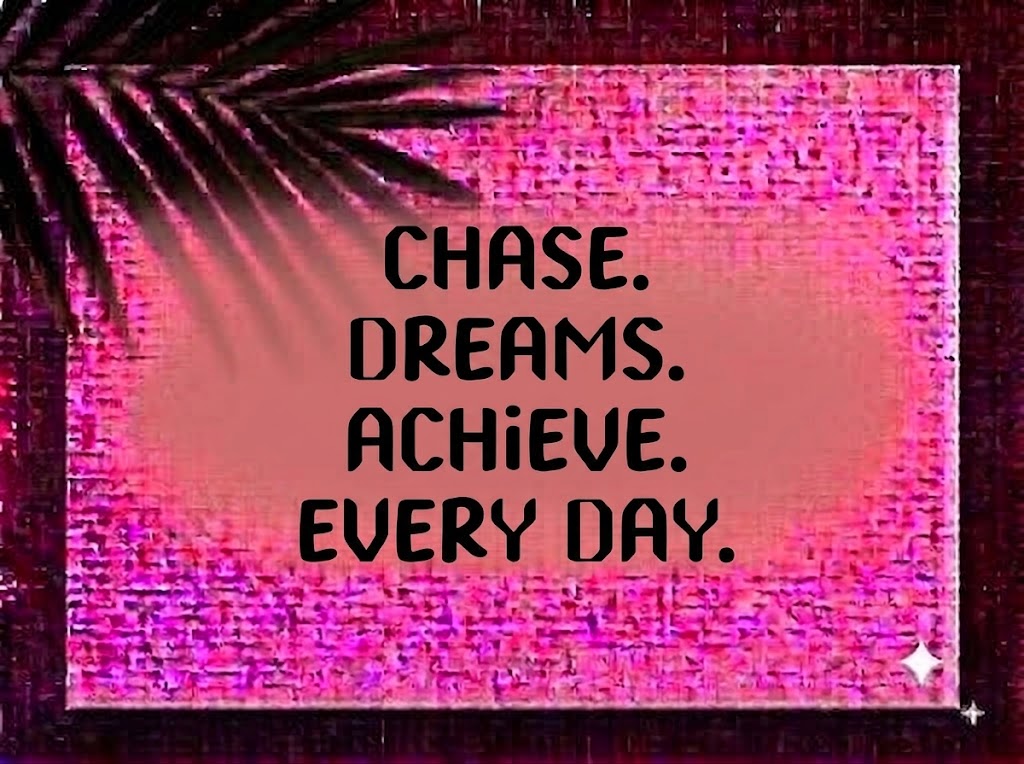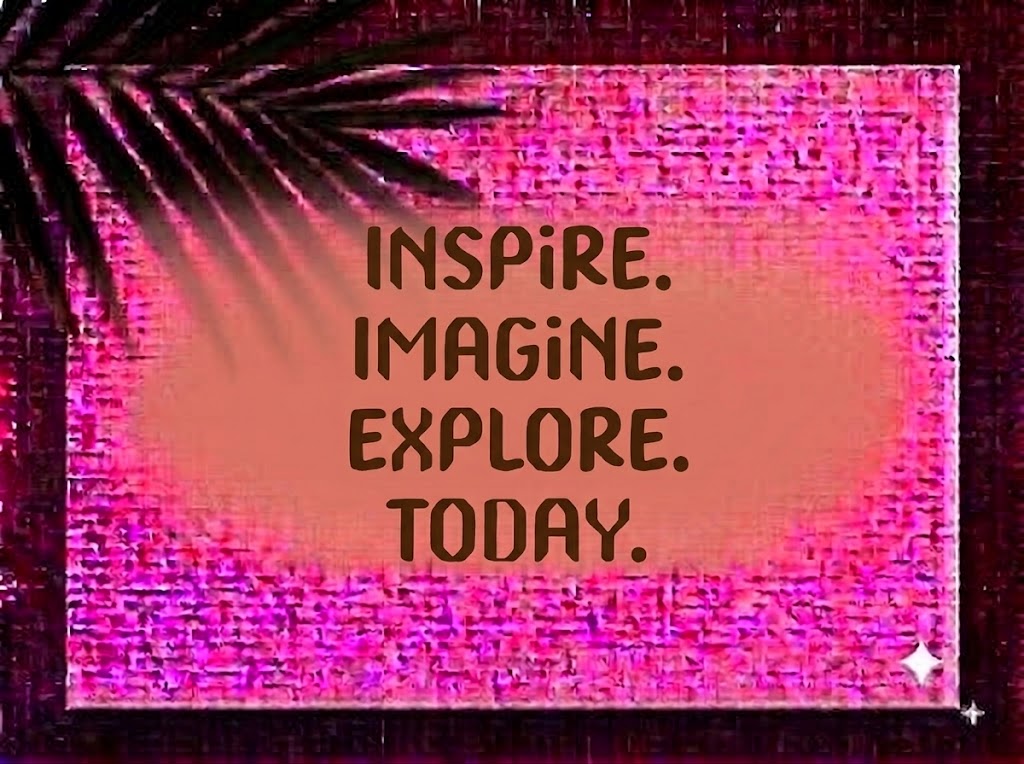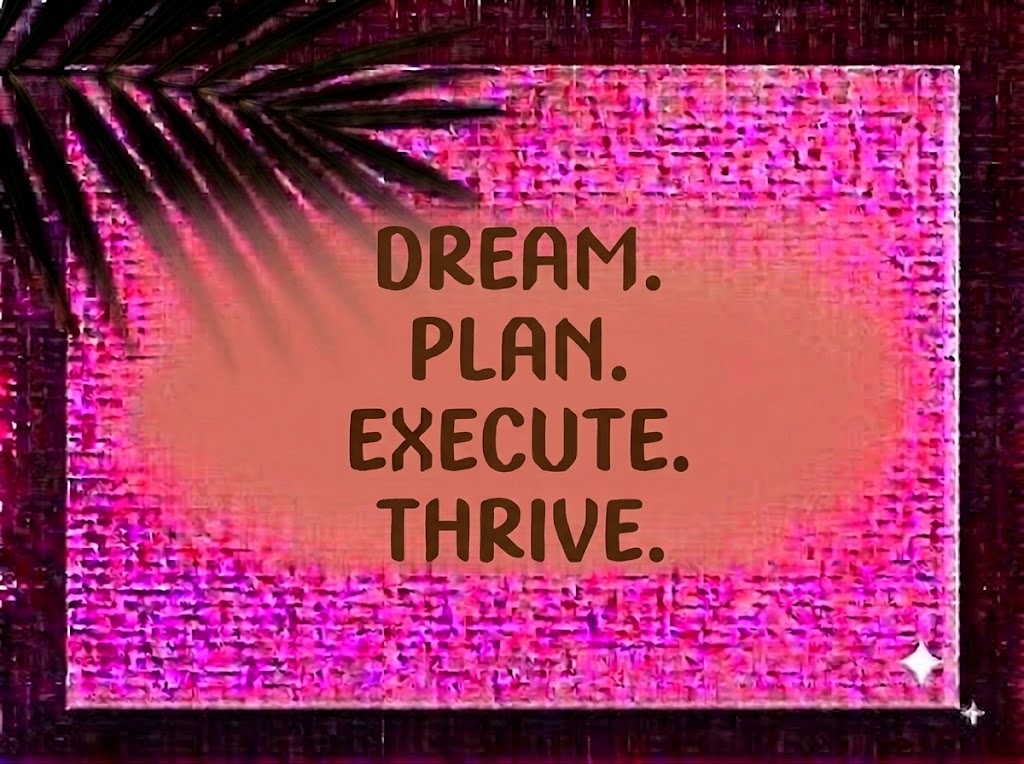
1FTV Sagitarion
Trong xu hướng thiết kế đồ họa thị giác và sáng tạo nội dung đương đại, các phông chữ mang âm hưởng thần thoại, kỳ ảo (Fantasy) kết hợp cùng tinh thần Retro/Vintage của thập niên 70 đang trở lại vô cùng ấn tượng.
Nếu bạn đang tìm kiếm một phông chữ hiển thị độc lạ, mang đậm màu sắc chiêm tinh học, huyền bí để làm bìa album âm nhạc, áo thun phong cách Gothic/Rock, poster phim ảnh hay tiêu đề video ngắn bùng nổ, font 1FTV Sagitarion chính là sự lựa chọn không thể bỏ qua.
Giới thiệu về font 1FTV Sagitarion
Font 1FTV Sagitarion là bộ chữ hiển thị trang trí (display font) lấy cảm hứng từ biểu tượng cung hoàng đạo Nhân Mã (Sagittarius) và nghệ thuật typography phong cách Art Nouveau/Psychedelic cổ điển:
Tên phông chữ: 1FTV Sagitarion
Đặc điểm nổi bật của phong cách thiết kế Sagitarion
Sức hút thị giác của font 1FTV Sagitarion đến từ sự pha trộn độc đáo giữa cấu trúc chữ thon gọn và các đường nét biến điệu uốn lượn đầy mê hoặc:
Phom dáng thon cao (Condensed & Tall Display): Thân chữ vươn cao giúp tối ưu hóa không gian theo chiều dọc, cho phép bạn đưa các câu tiêu đề dài vào khung hình mà vẫn giữ được độ thoáng và tính bề thế.
Định dạng All-Caps kiên cố: Toàn bộ hệ thống ký tự được xây dựng đồng nhất theo phom dáng in hoa, tạo nên một dải khối vững chãi, bắt mắt và thu hút sự chú ý ngay từ cái nhìn đầu tiên.
Khoảng cách ký tự (Kerning): Khoảng cách giữa các chữ cái được tính toán tỉ mỉ, giúp các đường nét uốn lượn và chân loe khi đặt cạnh nhau không bị va chạm hay gây rối mắt.
Bản Việt hóa chuẩn chỉnh: Hệ thống dấu thanh tiếng Việt (sắc, huyền, hỏi, ngã, nặng, mũ, móc) được trau chuốt đồng điệu với cấu trúc thon mảnh của thân chữ, đặt đúng trọng tâm thị giác giúp các câu tiếng Việt giữ trọn vẻ đẹp thanh thoát và ma mị.
Hệ thống ký tự đồng bộ: Tích hợp trọn vẹn bộ chữ cái, dãy số 0-9 cùng đầy đủ các ký hiệu toán học và dấu câu cơ bản.
Hình ảnh demo thực tế của font 1FTV Sagitarion
Khả năng hiển thị của phông chữ được tối ưu linh hoạt theo nhiều kích cỡ:
Kích thước nhỏ (12pt – 24pt): Cấu trúc chữ đứng ngay ngắn và độ đậm vừa vặn giúp các câu ngắn hay dãy số vẫn hiển thị rành mạch trên màn hình điện thoại di động.
Kích thước lớn (36pt – 72pt): Đây là đất diễn lý tưởng nhất để 1FTV Sagitarion phô diễn toàn bộ nét uốn lượn kỳ ảo, sự phóng khoáng và thần thái ma mị cho các dòng tiêu đề chính.
Ứng dụng trong thiết kế đồ họa và làm video
Sở hữu nét cá tính độc bản và giàu chất thơ huyền bí, font 1FTV Sagitarion mở ra không gian ứng dụng phong phú:
Video ngắn (TikTok, Reels, Shorts): Dáng chữ thon cao hiển thị rất cuốn hút trên khung hình đứng tỷ lệ 9:16. Cực kỳ ăn nhập với các video về chủ đề Tarot, chiêm tinh hoàng đạo, thần thoại, review phim kinh dị/kỳ ảo, podcast tâm sự hay clip nhạc Acoustic/Indie.
Ảnh thu nhỏ YouTube (Thumbnail): Lựa chọn hoàn hảo cho các kênh khám phá hiện tượng siêu nhiên, review truyện kỳ ảo, tử vi hoặc phân tích phim ảnh nhờ khả năng gây tò mò thị giác cao.
Thời trang Streetwear & Merchandise: Rất thích hợp in ấn lên áo thun Vintage, áo phông Band nhạc Rock/Metal, áo hoodie, túi tote hay các phụ kiện mang phong cách Bohemian, Gothic.